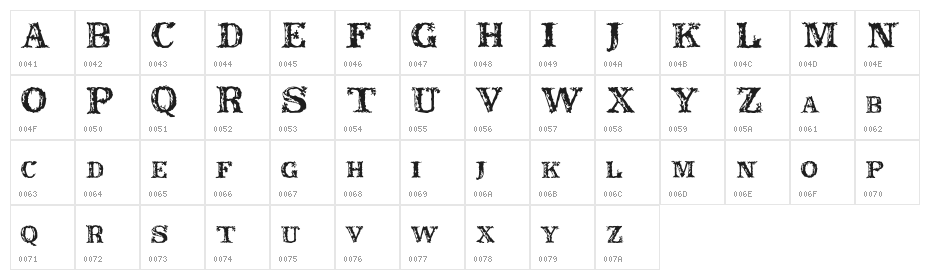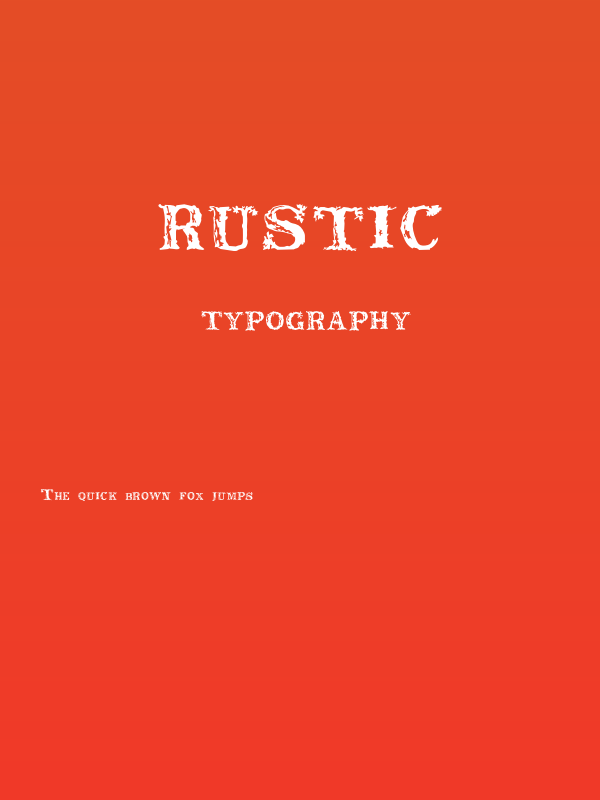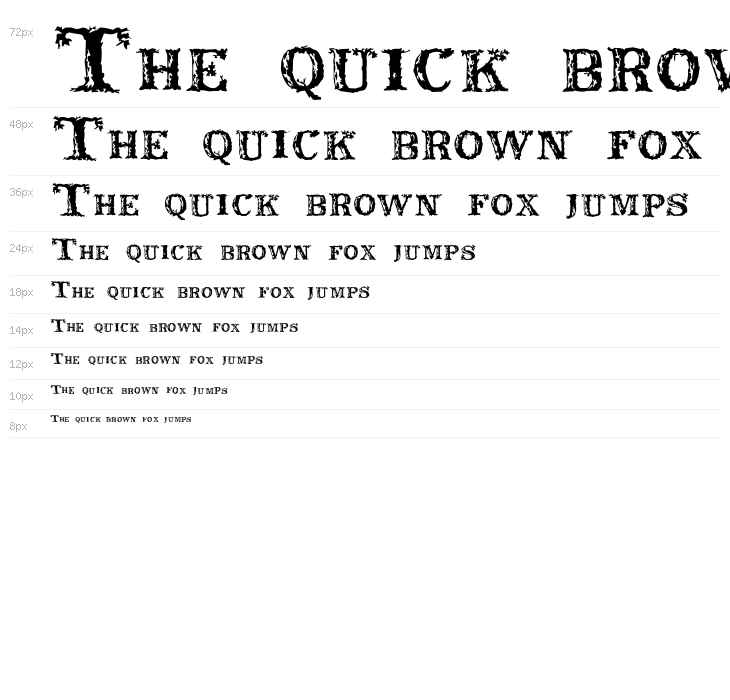
Rustic Font
| Общий стиль | Rustic, Vintage |
| Рекомендуемые проекты | Ideal for vintage-themed posters, rustic branding, outdoor event invitations, or any project seeking an authentic, handcrafted look. |